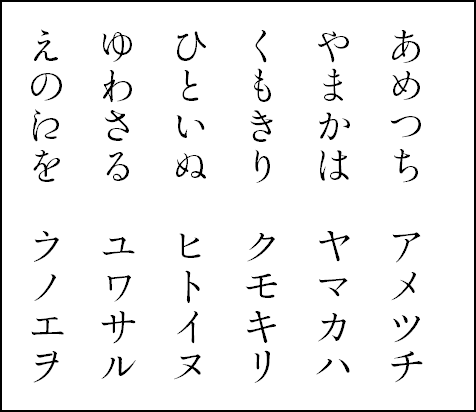
5. フォント
Unicode 6.0.0より使用可能となった次の仮名2文字が含まれるフォントの配布ならびに情報を公開しています。
- 𛀁𛀁: U+1B001; HIRAGANA LETTER ARCHAIC YE(ヤ行のエを表した「江」に由来する平仮名。「エ」のひらがな版)
- 𛀀𛀀: U+1B000; KATAKANA LETTER ARCHAIC E(あ行のえを表した「衣」に由来する片仮名。「え」のカタカナ版)
活字例
U+1B000のほうは「フ」の上に「ヽ」という比較的単純な図形ですが、U+1B001のほうは少し字の骨格が摑みにくいようなところがあります。そこでフォント作りをなさる方向けに、当方で参考にしたこの字の活字例を載せておきます。
- 明朝:
- ゴチ:
出典はともに錦明朝かなの参考文献として記載されている見本帳です。
OS添付フォント
2012年3月1日現在、前年にリリースされたWindows 8 Developer Previewに引き続き、2012年2月29日(米国時刻)にリリースされたWindows 8 Consumer Previewのメイリオにも𛀁と𛀀とが含まれていることを確認済みです。
一方MS明朝・MSゴシック系にはDeveloper Previewの時と同様に含まれていません。